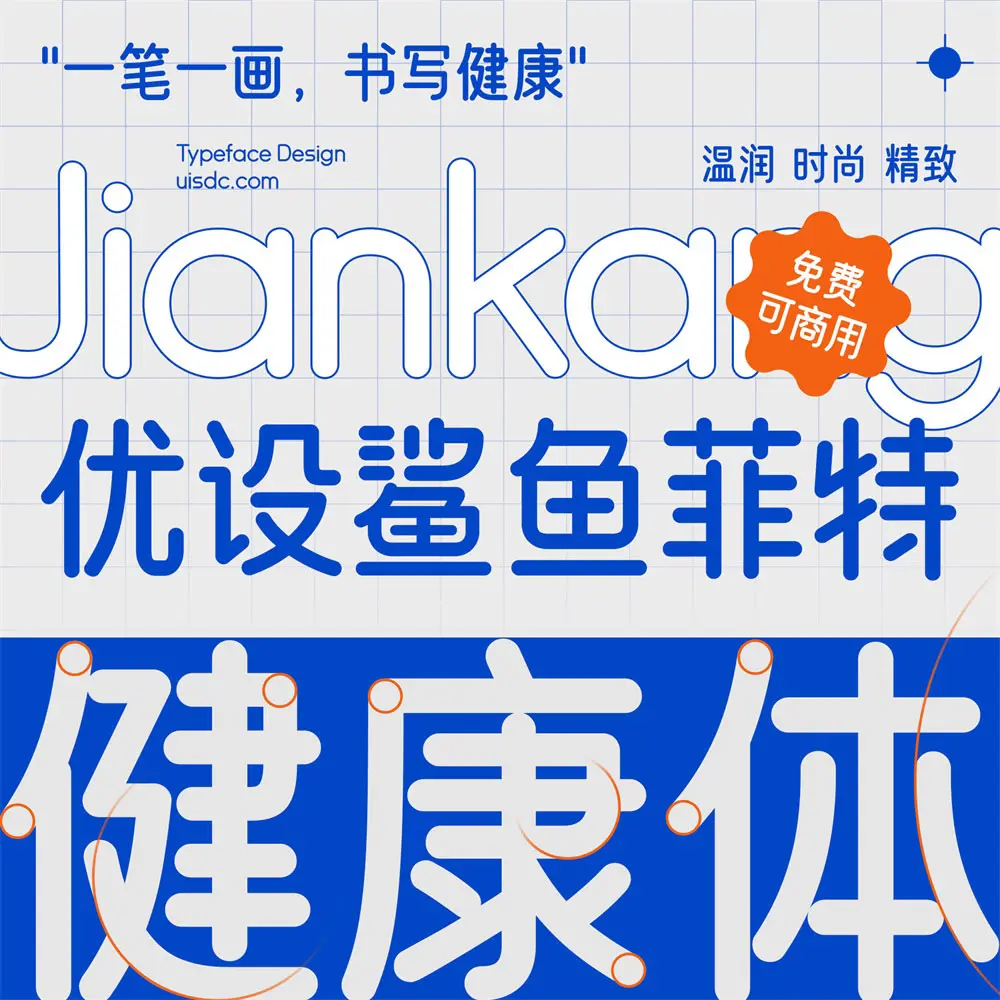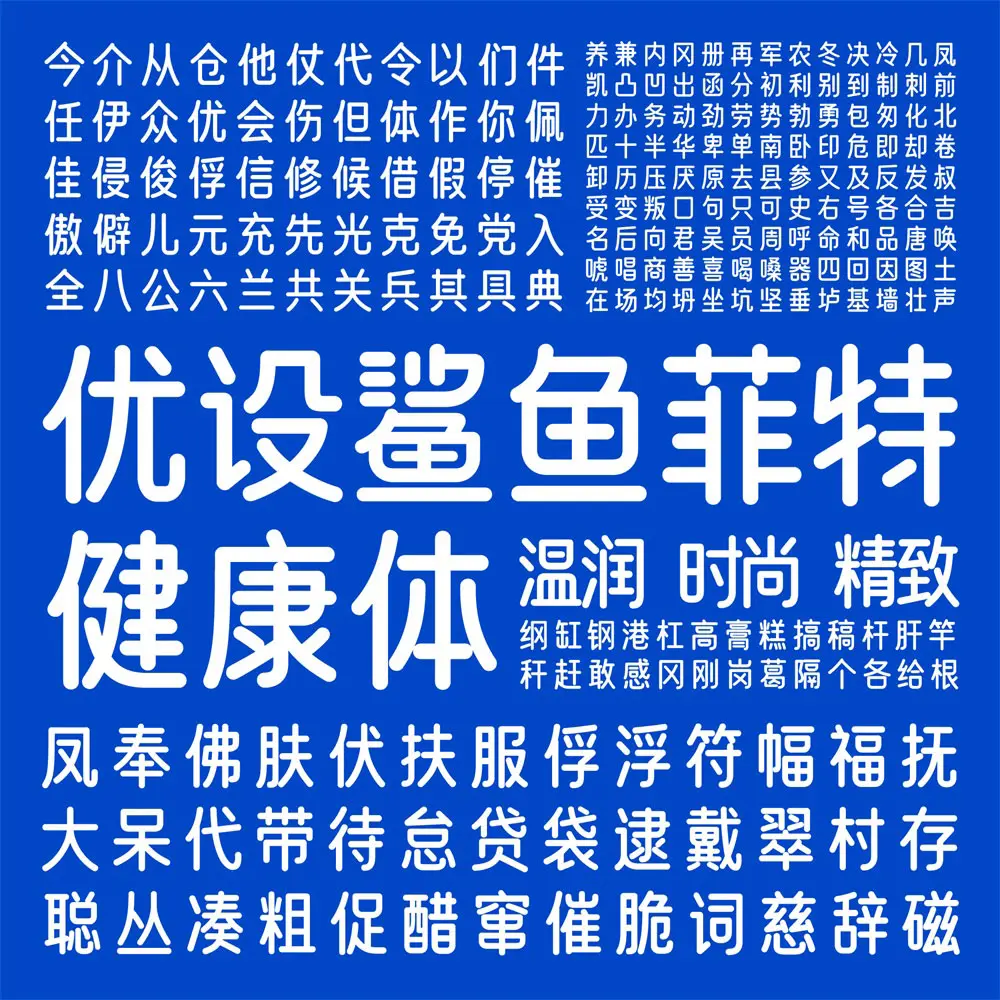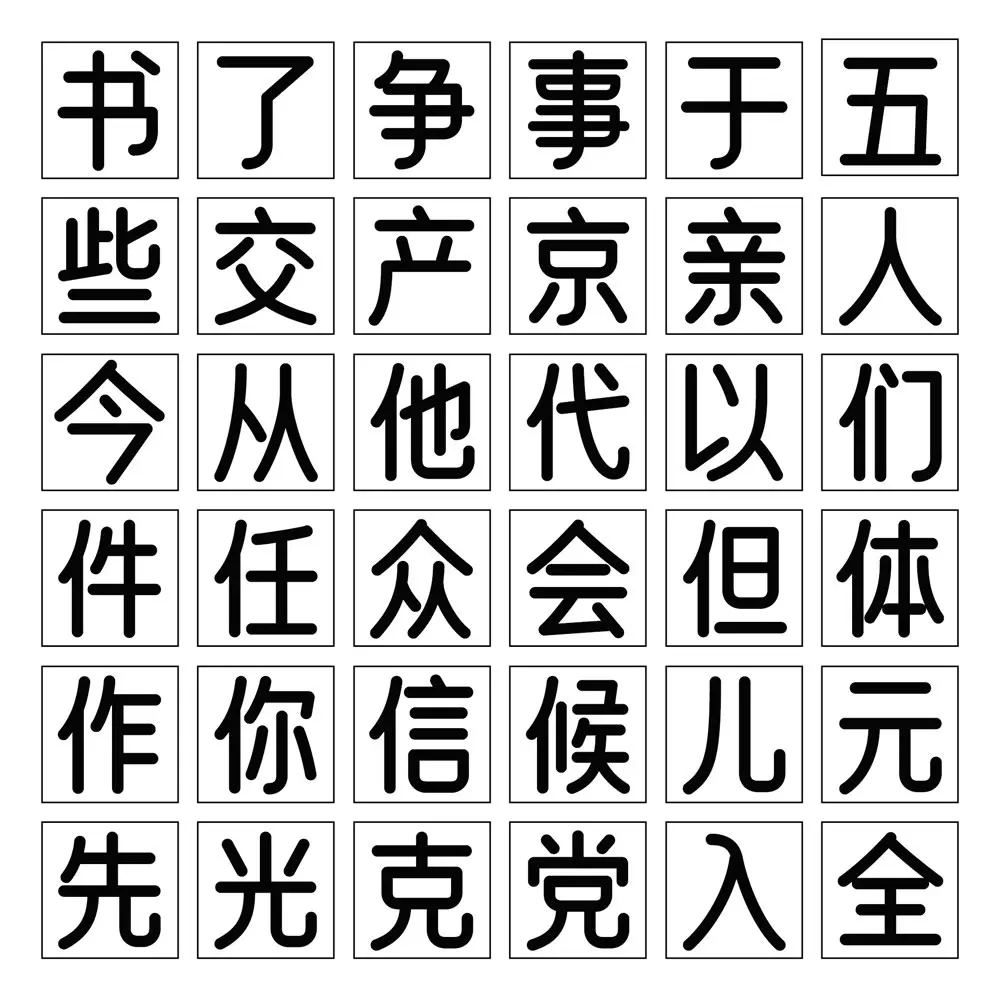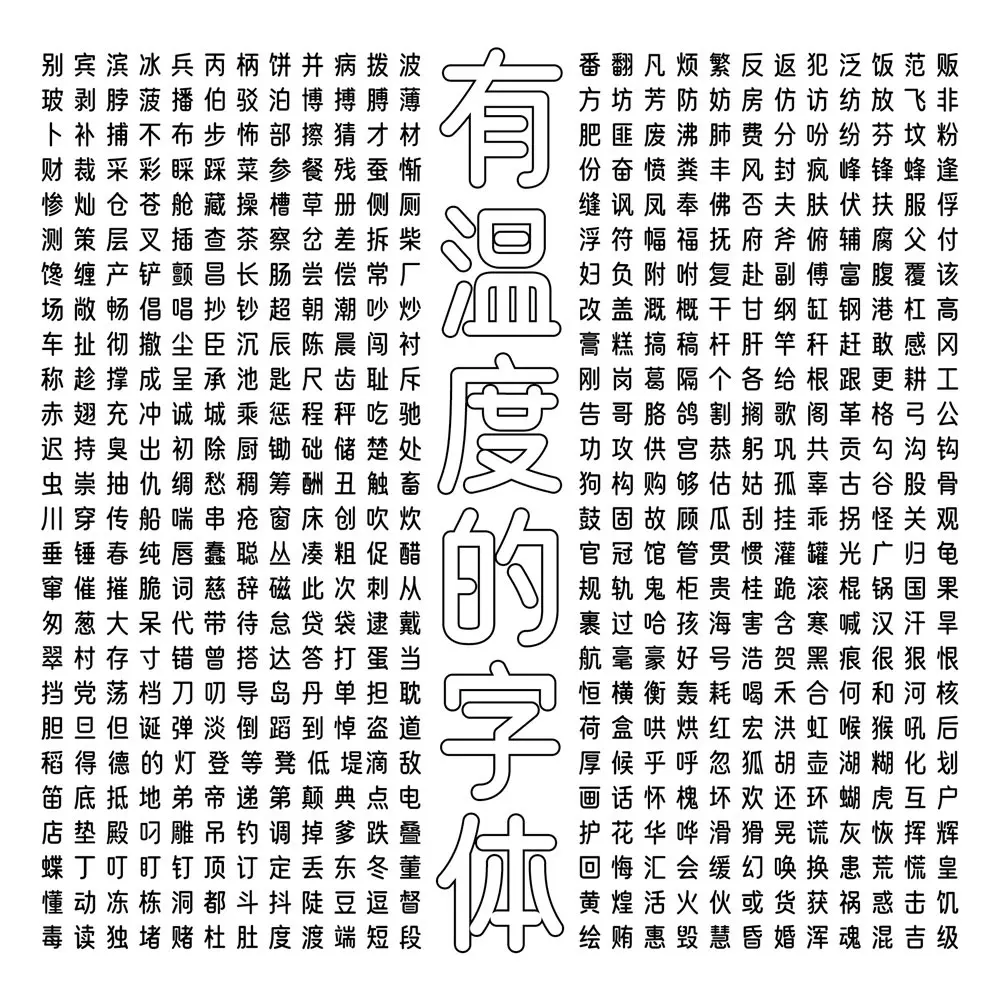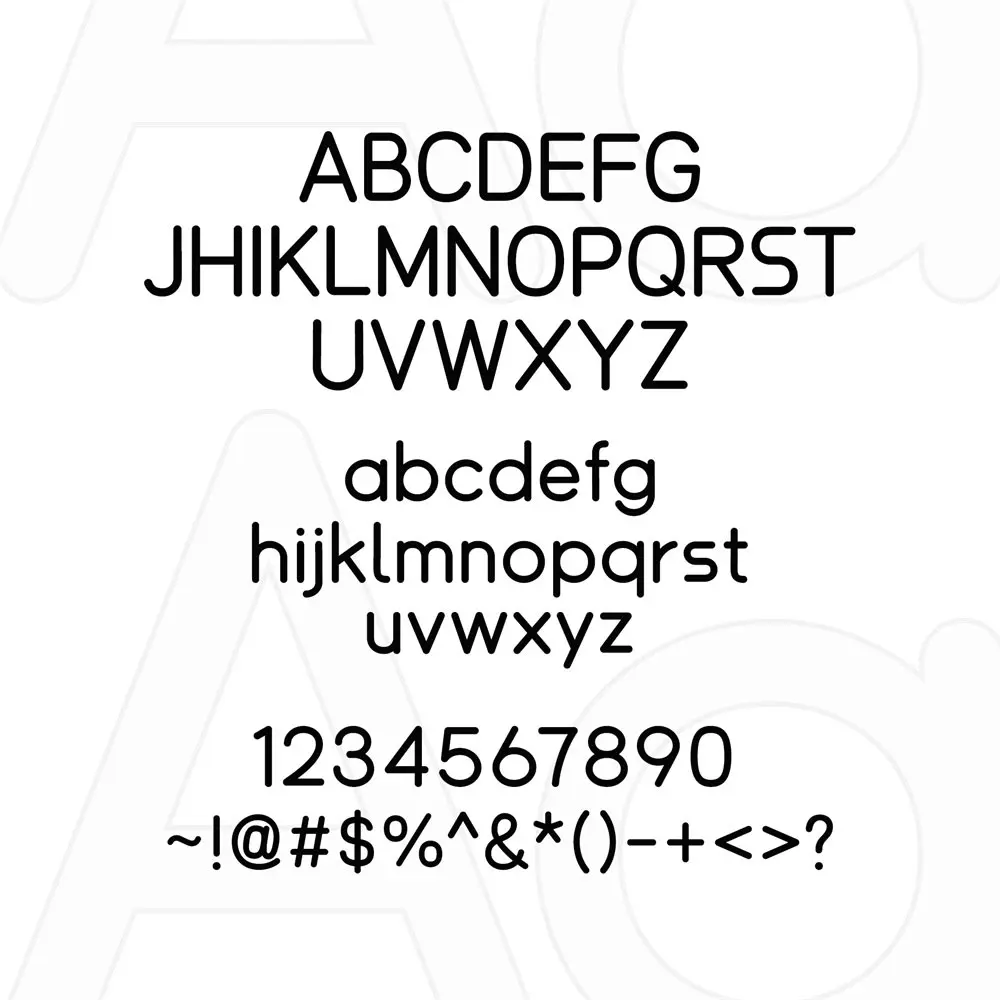
優設鯊魚菲特健康體是由字繪中國發起,新零售健康輕食品牌鯊魚菲特聯合優設與字由,為廣大設計師特推出了一款專為健康而生,電商應用場景極強的優質字體。
優設鯊魚菲特健康體是優設好身體的升級版,造型上要比優設好身體更具有辨識度,設計上更加貼近健康品牌附有的親和力和現代感,不僅會成為電商設計的又一大助力,更體現了當下追求健康的年輕用戶群體特性。
字體設計之初是作為健康輕食品牌“鯊魚菲特”的品牌 logo 去創作設計的。在符合當下追求健康的年輕用戶群體調性的同時保持了品牌親和力。
現整套字體在原有圓體圓潤的外觀和優美的弧度下,對字形、筆畫細節進行再設計,結構縱向拉長,體現健康體態的纖細勻稱感;同時在一些筆劃轉角、弧度控制曲線讓細節之處富有一些硬挺的視覺感受。使字體整體風格更輕快時尚又不失精緻與穩重感。